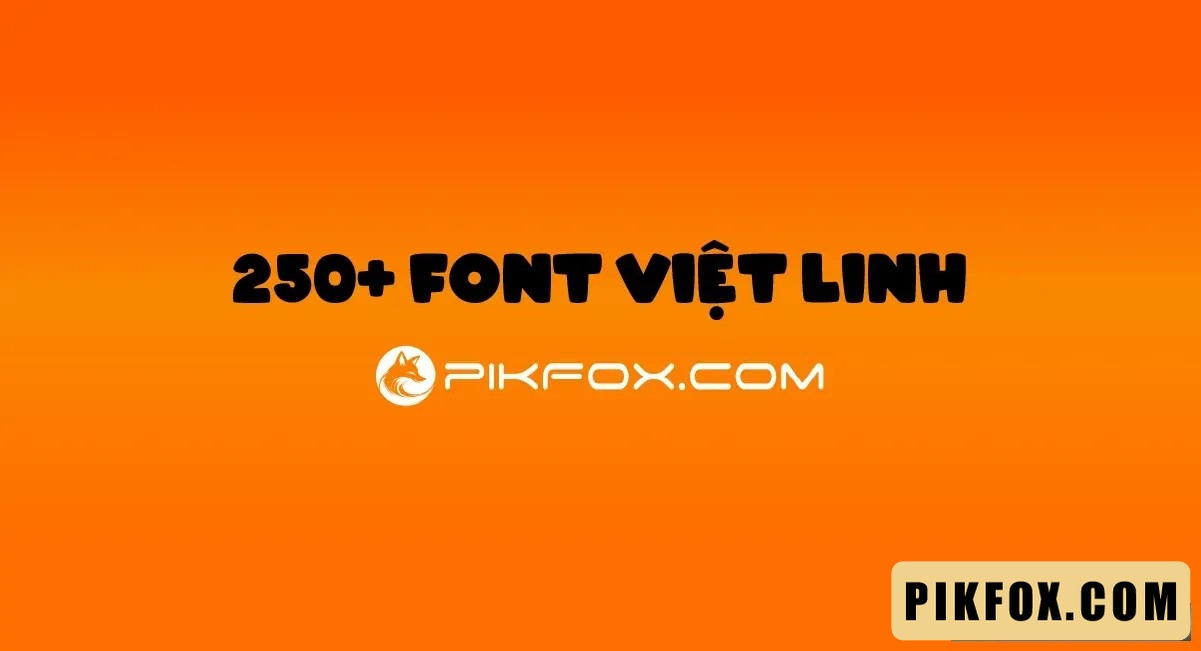
250+ Font Việt Linh
Bộ sưu tập 250+ font Việt Linh cung cấp đa dạng phong cách chữ viết, phù hợp cho nhiều loại hình thiết kế như banner, poster, thiệp mời, ấn phẩm truyền thông và trang trí sự kiện. Với dung lượng 46 MB, bạn có thể dễ dàng tải về và tùy chỉnh font chữ theo ý muốn để tạo ra sản phẩm độc đáo.
- Hơn 250 mẫu font chữ Việt Linh.
- Phù hợp cho in ấn, truyền thông, thiết kế website và trang trí.